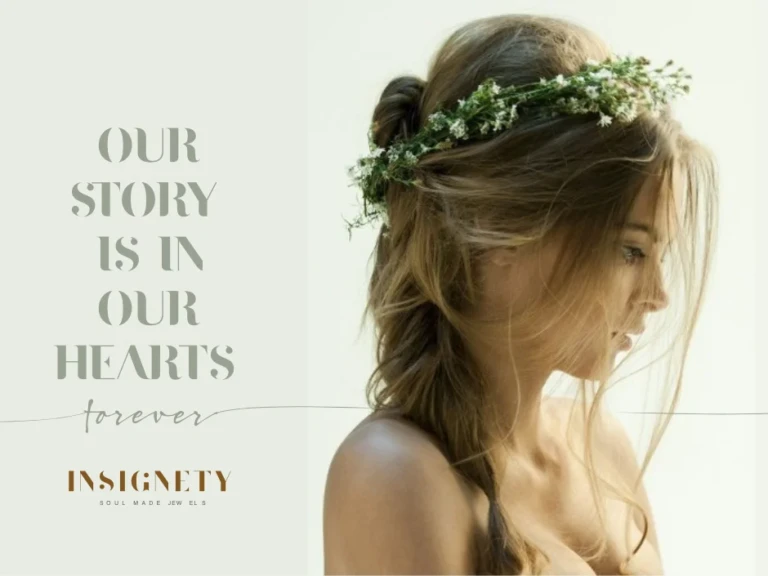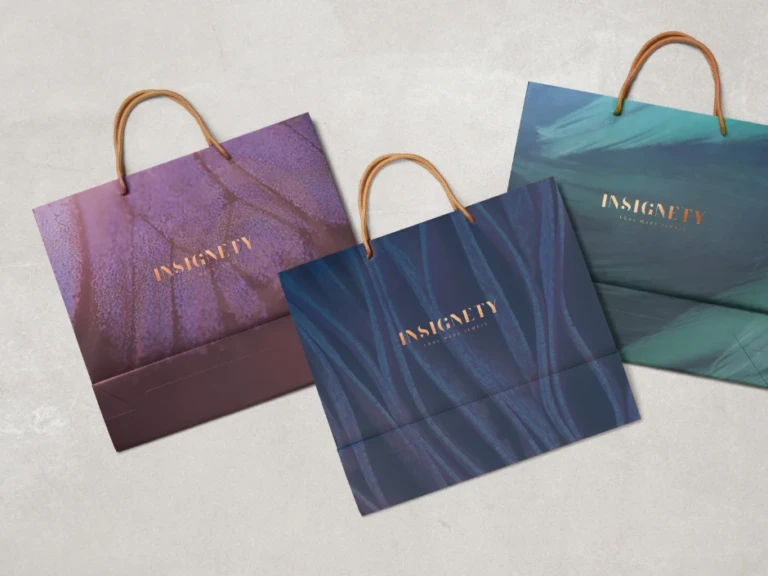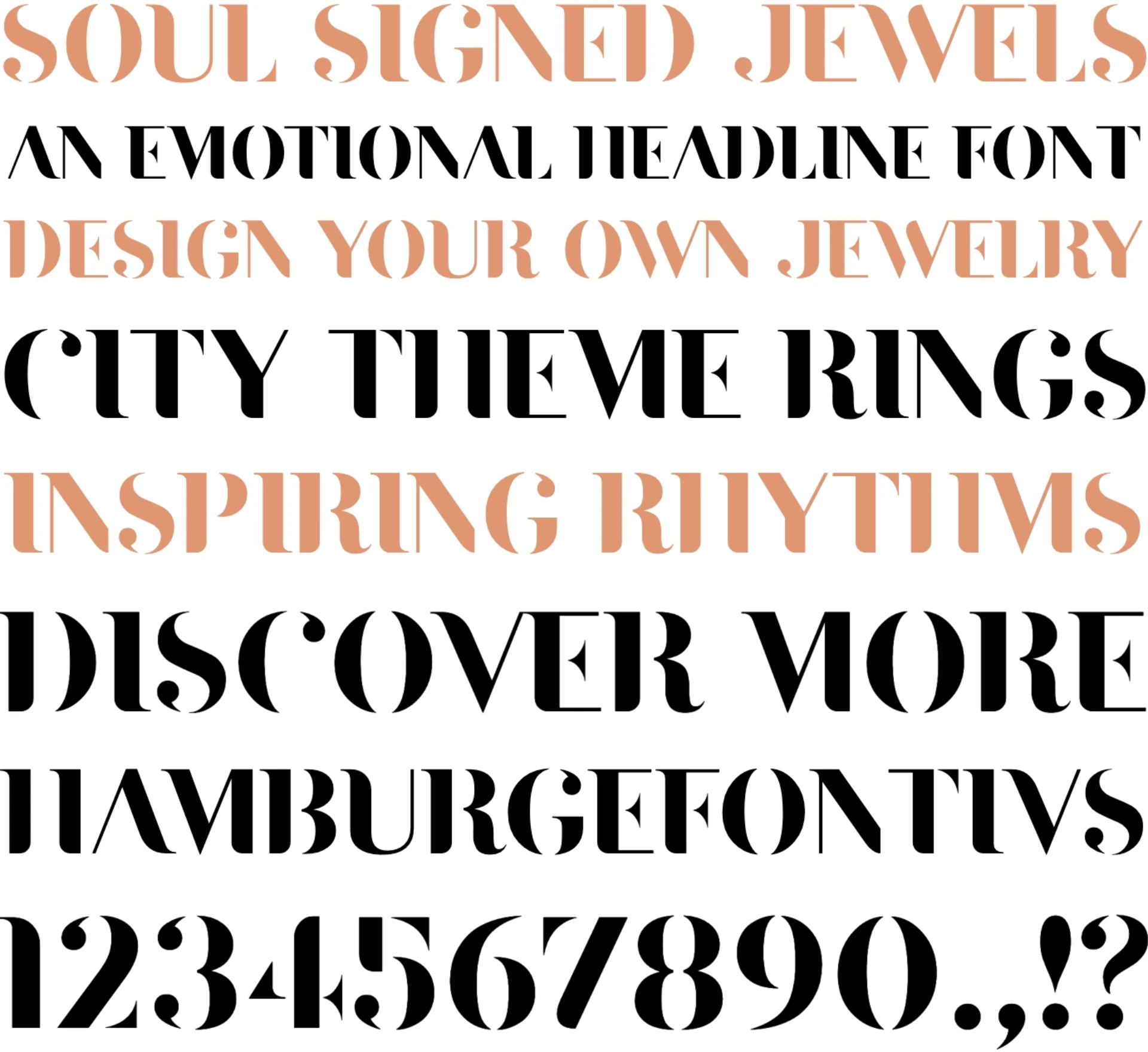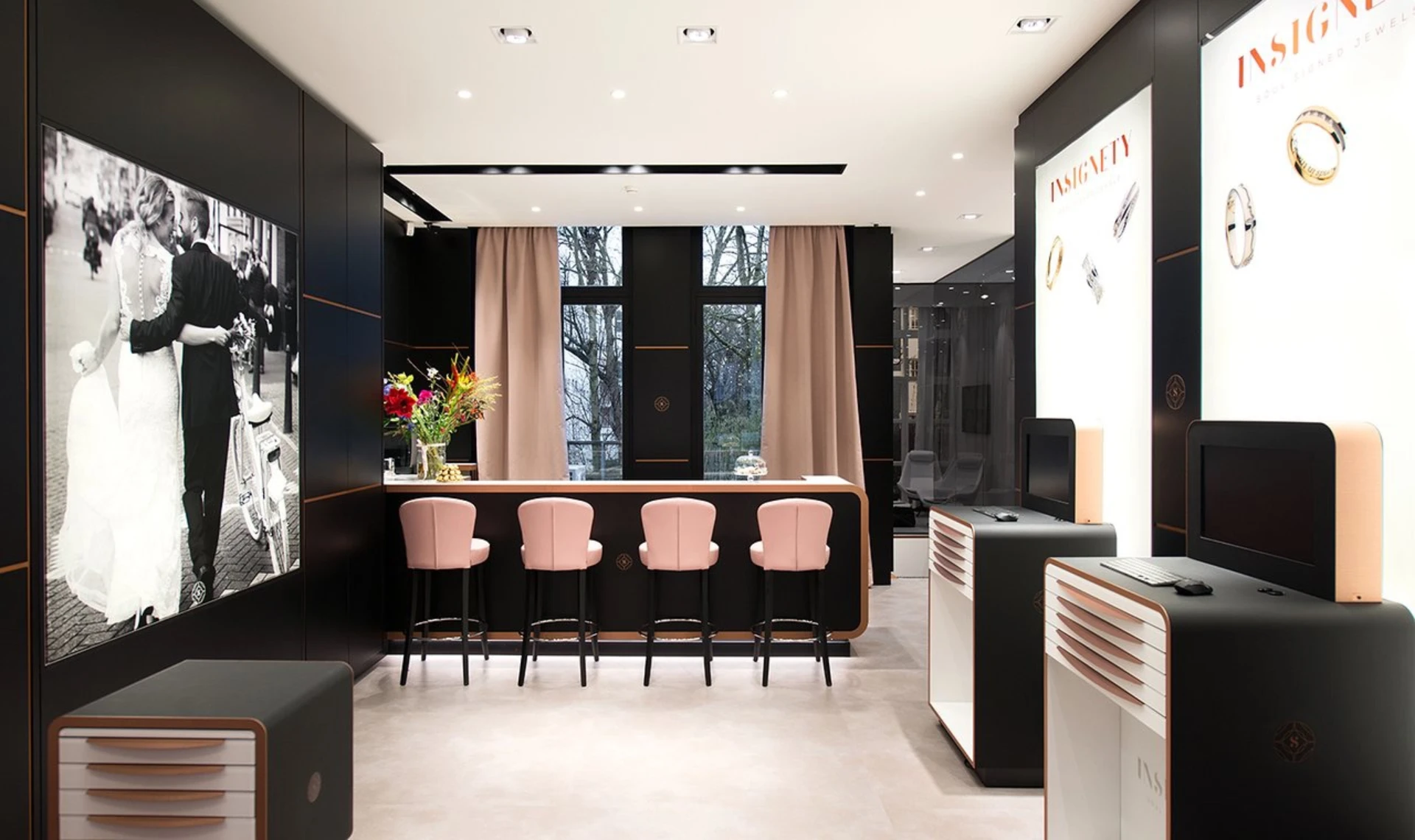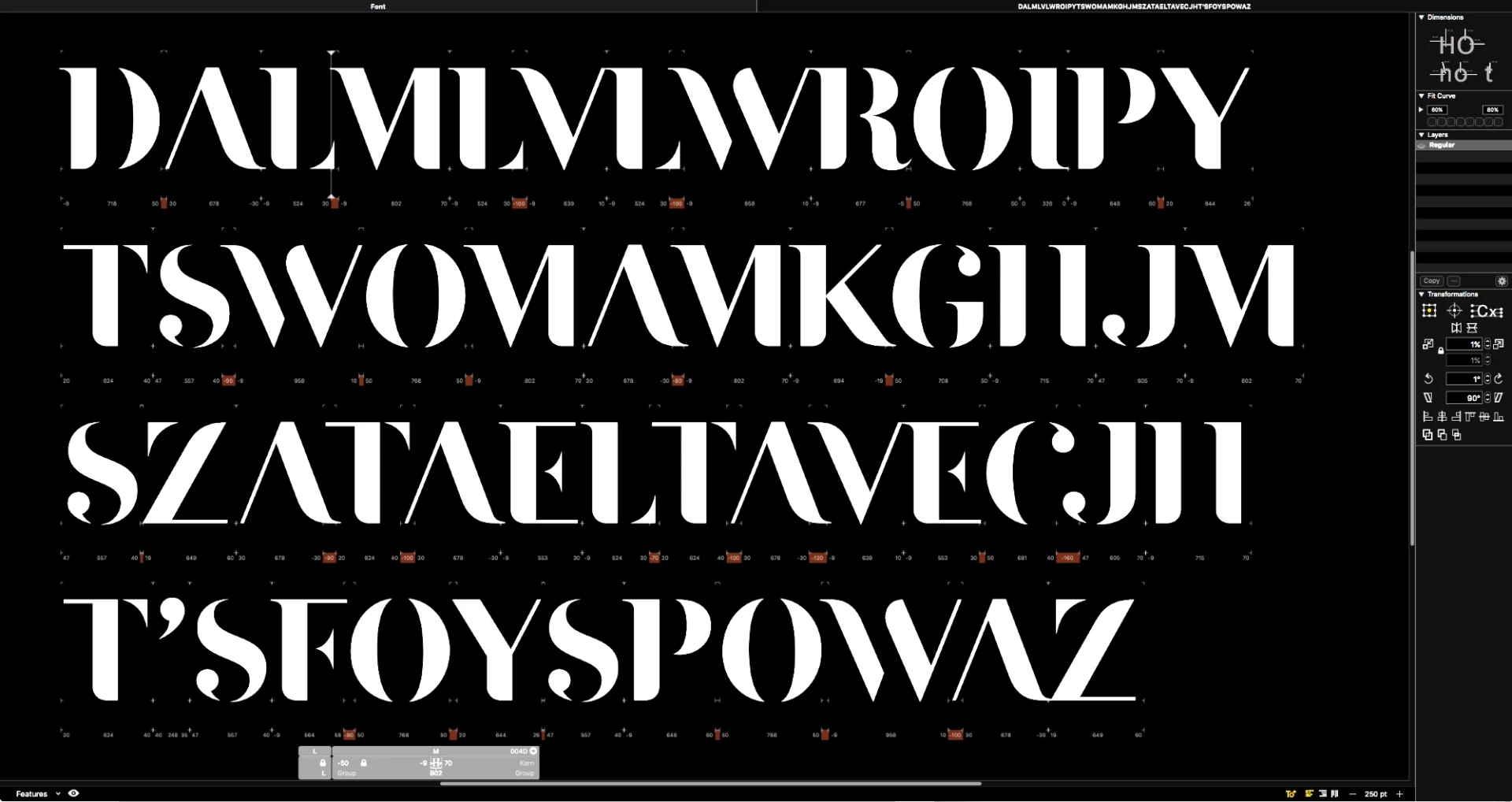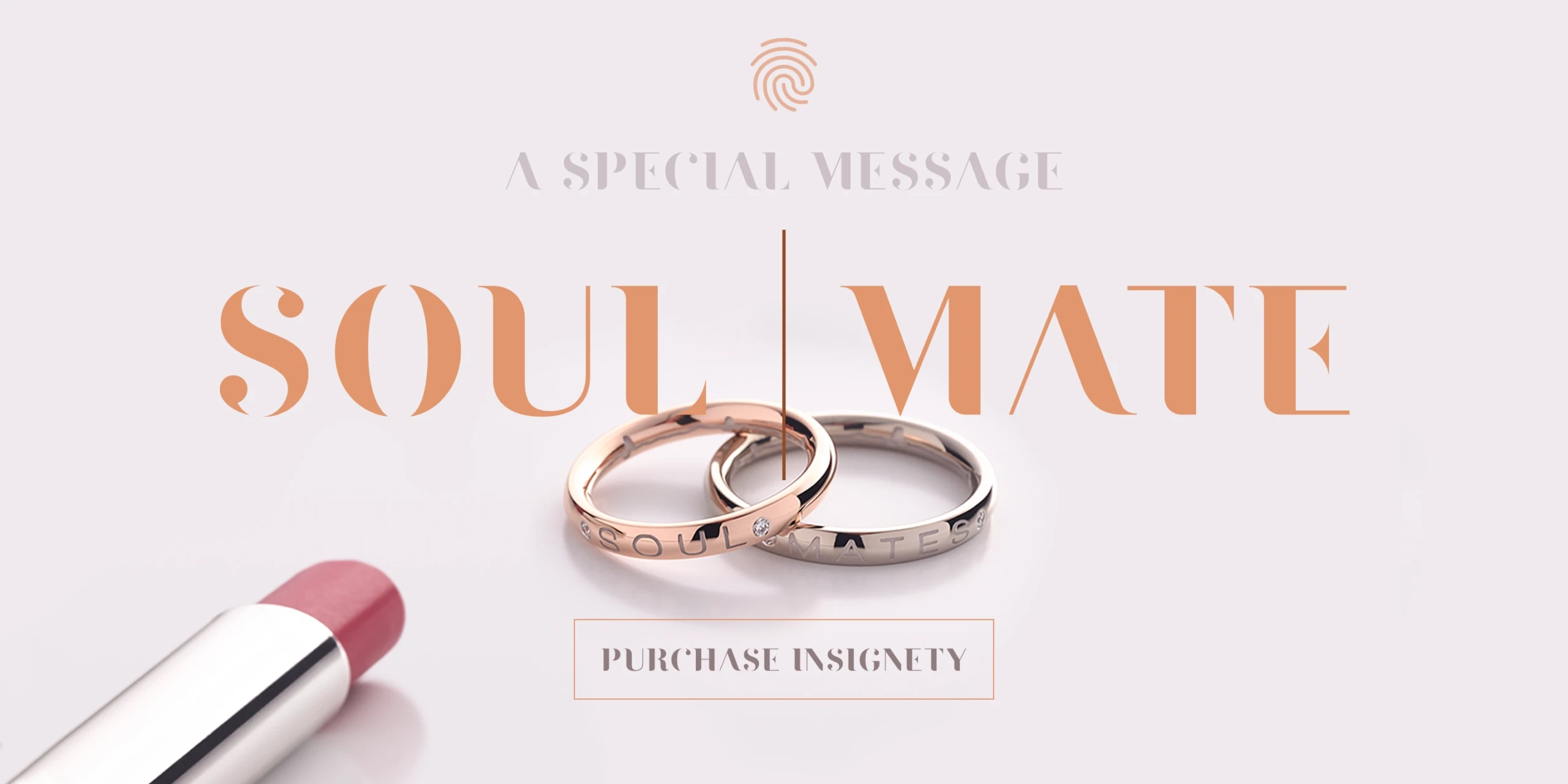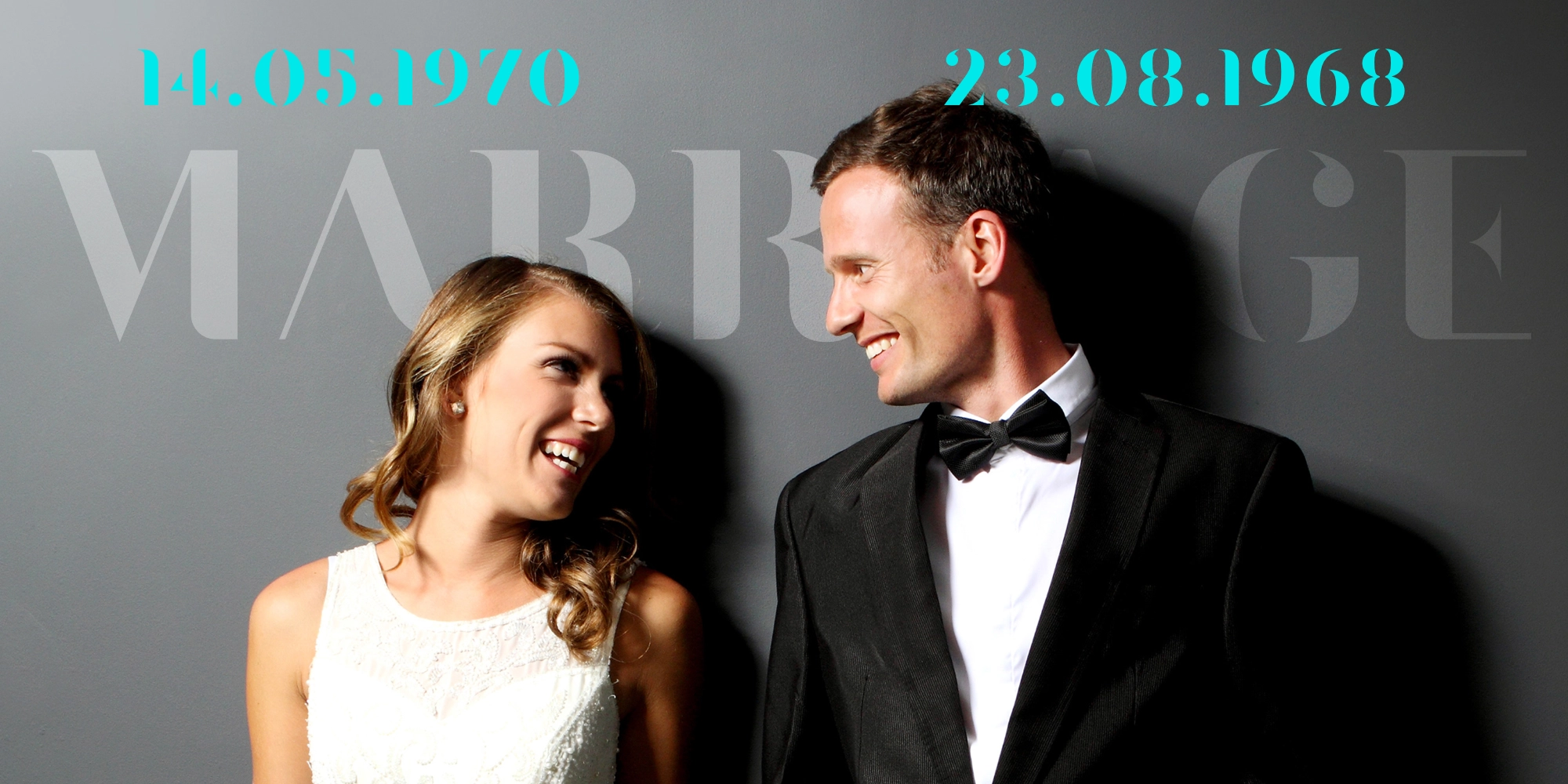
Insignety Amsterdam custom font
Het Insignety Amsterdam custom font is een soulful brandfont voor de juwelier ‘Insignety’. Ze bieden een hoogwaardige sieradencollectie en innovatieve ontwerpoplossingen voor in de winkel, waarbij vaardigheden uit de gouden eeuw worden gecombineerd met nieuwe technologie. Insignety gaf ons de opdracht om een handgemaakt brandfont te maken dat bij hun product past: sieraden op maat.
Een font met klasse, verfijnd en een tikkeltje mysterieus
Insignety Amsterdam gewichten stijlen
Insignety zal slechts in één gewicht verkrijgbaar zijn met een beperkte tekenset:
Insignety heeft slechts één OpenType feature, afgestemd op de manier waarop het wordt gebruikt in web- en printtoepassingen:
- Stylistic Sets
Insignety is op maat gemaakt, gebaseerd op de wensen en branding richtlijnen van de klant. Daarom heeft het beperkte ondersteuning voor de Latijnse taal: